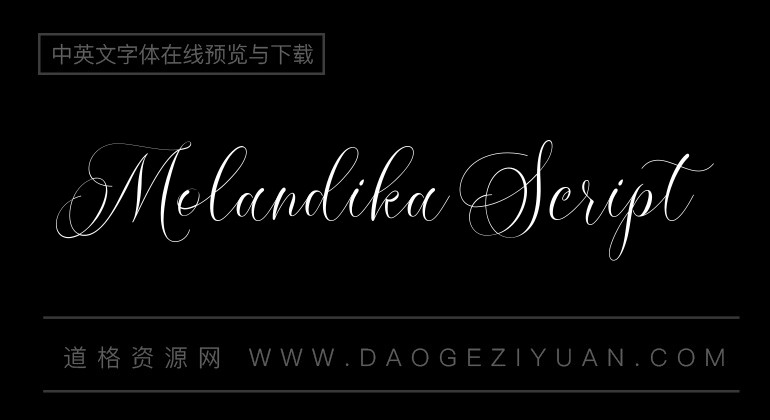
Molandika Script
Molandika Script 是一款自然、优雅的手写脚本字体,由 Molandika 的设计师 Mika Melvas 创作。它具有细腻的笔画,曲折的线条,流畅的字形,以及充满活力的笔触,让文字充满活力和自然的感觉。Molandika Script 字体适用于各种印刷和数字应用,可以用于标题、标签、海报、婚礼、商标、网站、卡片等等。它可以帮助你轻松地创建独一无二的设计,令人印象深刻。
Molandika Script是一款非常不错的手写艺术字体,具有很好的视觉感,适合于文化类的宣传设计、商业类品牌的广告和产品包装设计以及个性化文字排版等较多场景。